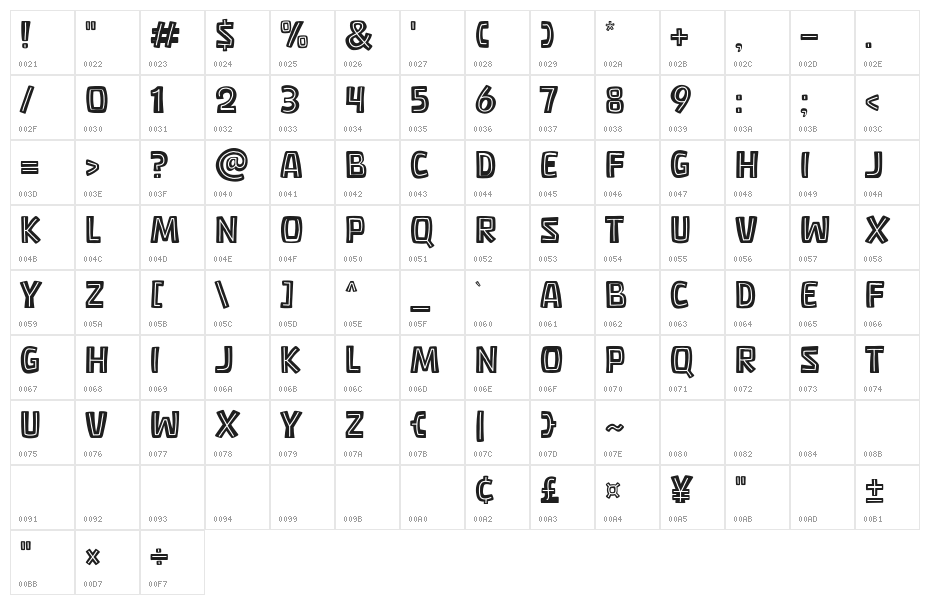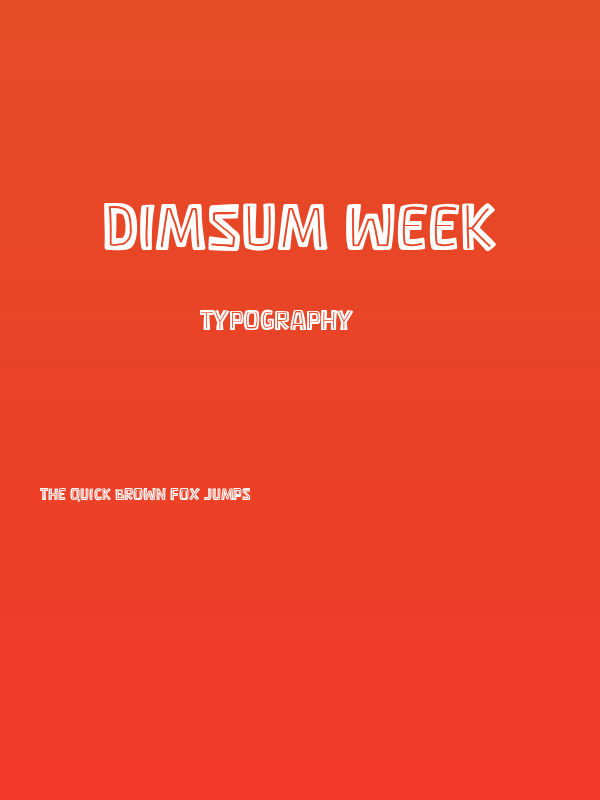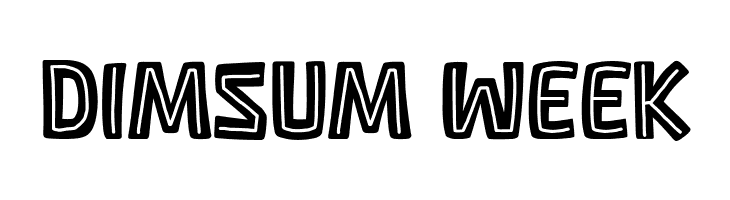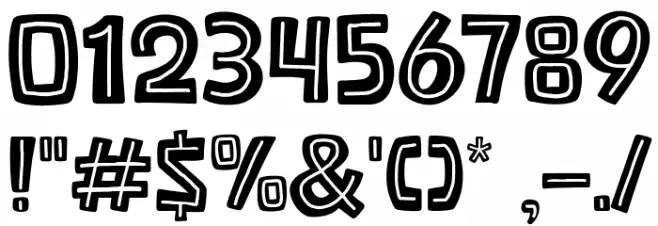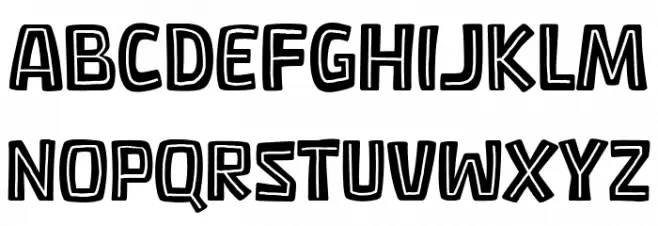
Dimsum Week Font
| Stil general | Playful, Hand-drawn |
| Proiecte propuse | Perfect for children's books, playful branding, posters, and event invitations. |